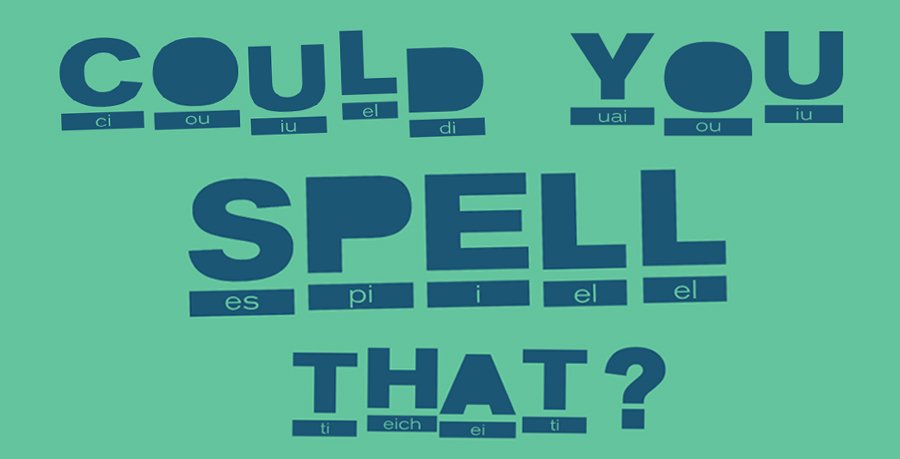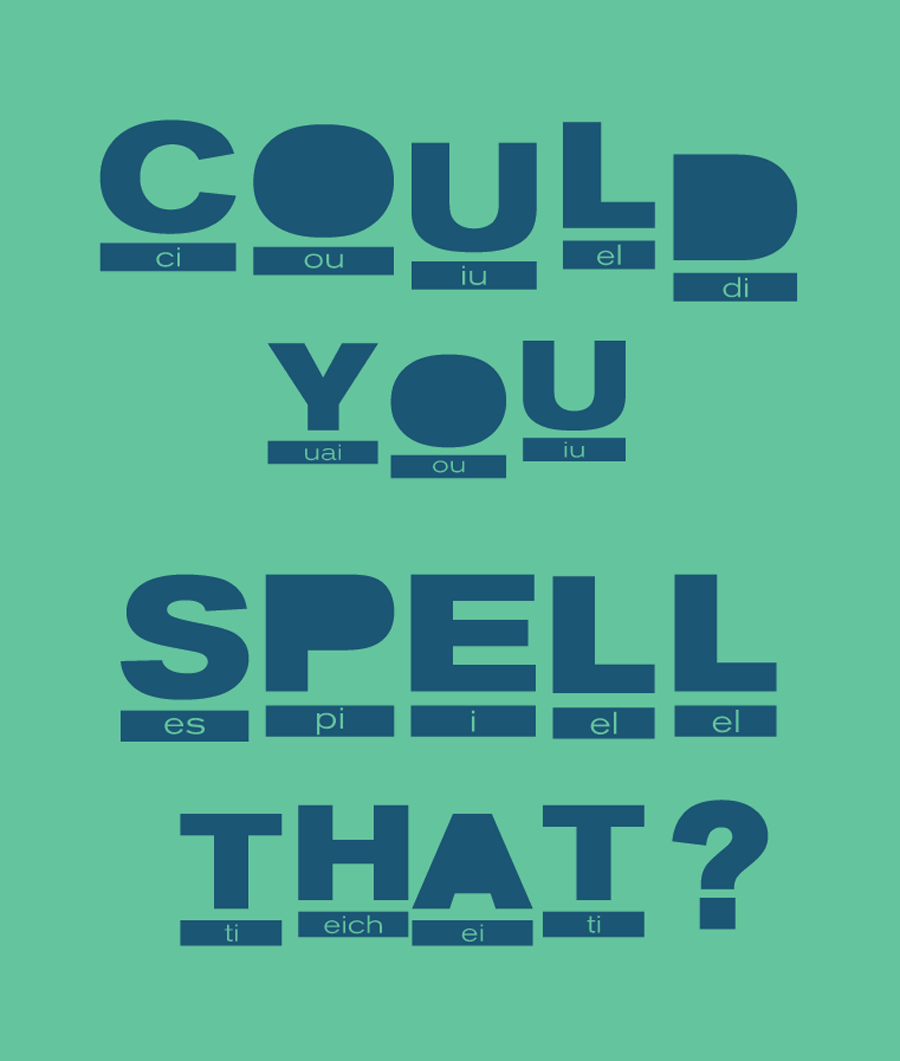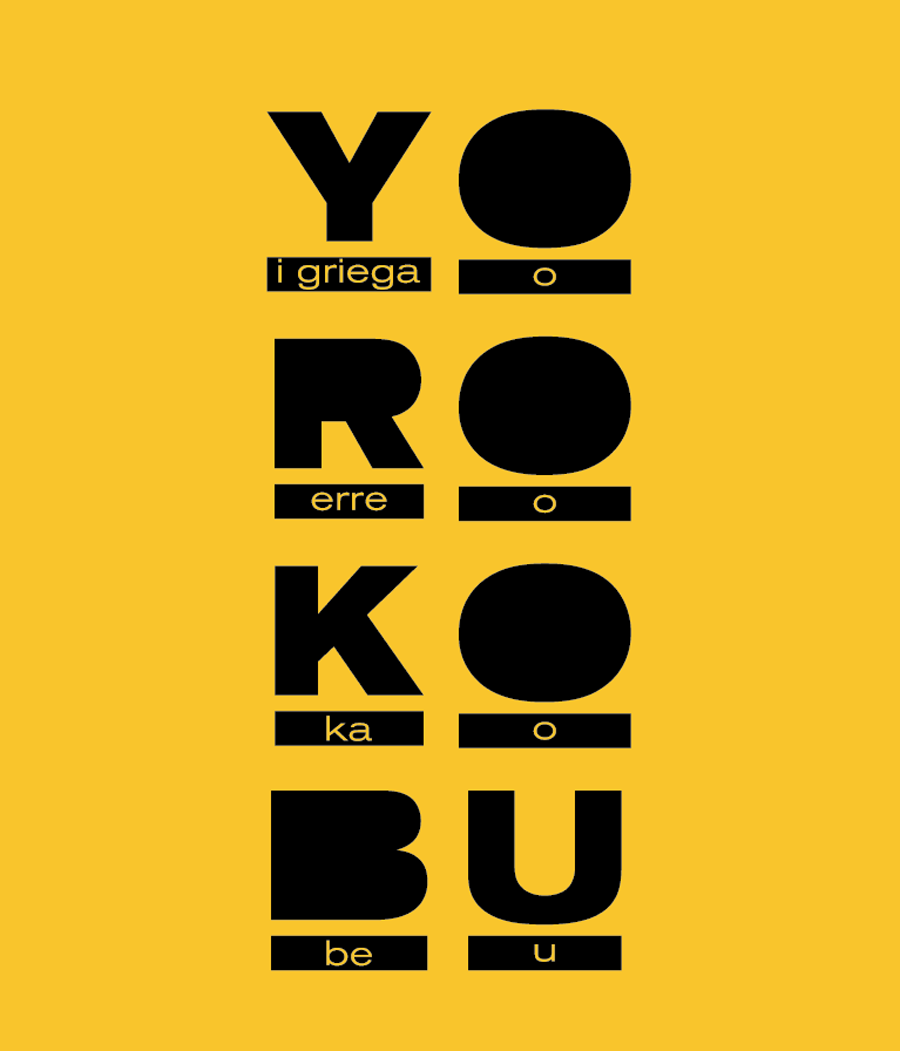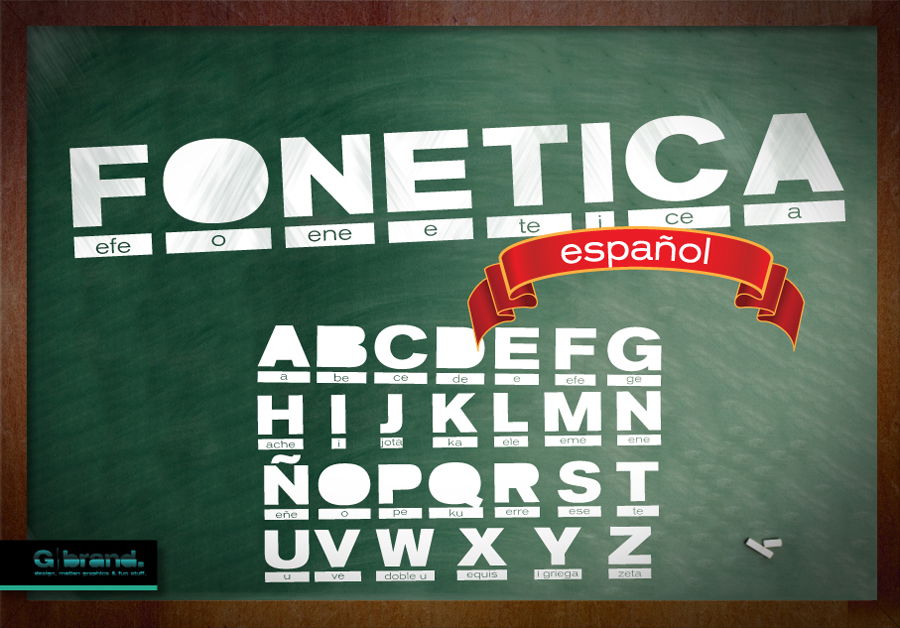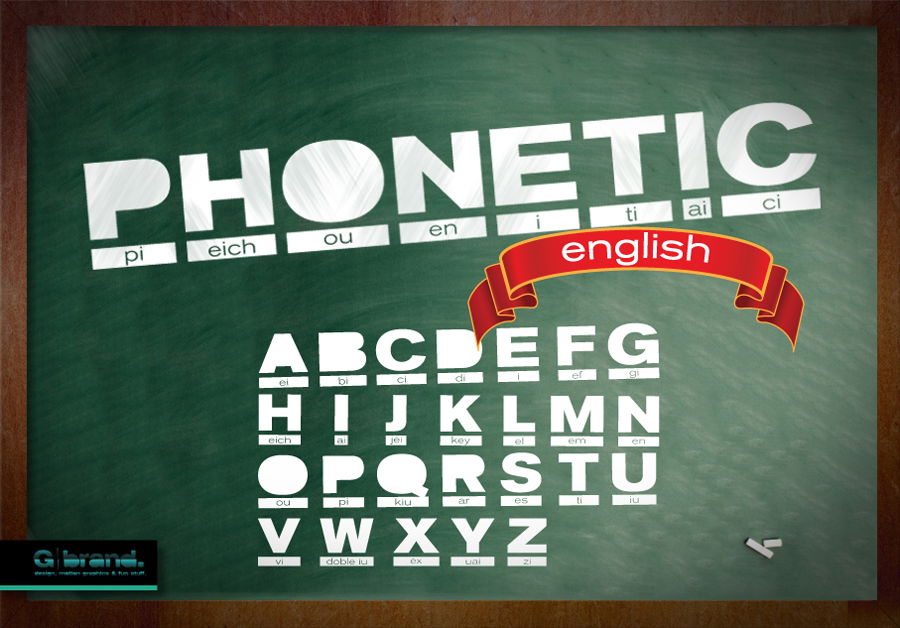
La tipografía que enseña inglés
Hay tipografías más grandes, más pequeñas, más lúgubres, más fiesteras, más anchas y más estrechas. También las hay muy ilustradas. O tan parcas que apenas se perfilan con un par de trazos. Gibrán Ramos (G Brand), un joven diseñador mexicano, ha inventado un tipo de letra para esos que siempre se liaron cuando les preguntaron aquello de “Could you spell that?” (¿Podrías deletrear eso?)
Phonetic (o Fonética) es una tipografía con intenciones de echar una mano a los que nunca contaron con el inglés entre sus fuertes. Cada letra de la fuente, además del caracter en sí, lleva de serie en su base la manera de pronunciarlo en el idioma de Shakespeare. No en fonética tradicional -que no todo el mundo sabe leer-, sino con la interpretación de los sonidos desde la pronunciación mexicana escrito con todas sus letras. Es decir, que B es ‘bi’, P es ‘pi’, Q es ‘kiu’ y la H se subraya con ‘eich’.
“A mí siempre me ha gustado explorar técnicas nuevas, aprender mas cosas”, dice este diseñador que por primera vez se ha aventurado en el mundo de las tipografías. “Se me ocurrió empezar con algo diferente porque no solo quería aportar una tipografía bonita, trataba de buscarle el giro”.
Ramos describe su creación como “un concepto simple, pero diferente”. “Es una tipografía de la familia San Serif (palo seco) a la cual le quité el blanco interno y le añadí en un rectángulo la pronunciación de la misma”. “No es nada fuera de este mundo, pero podría ser de utilidad para muchas personas, incluyéndome”.
Para que la funcionalidad de Phonetic fuera bidireccional, Ramos también creó la versión inversa, es decir, con la pronunciación fonética en castellano. Su propósito, según afirma, es que su aplicación no solo tenga “meros fines estéticos y gráficos, sino también educativos y didácticos”.
“Me gusta imaginar y me gustaría mucho ver qué tipo de diseños puede inspirar mi tipografía”, esgrime el creador, “y por otro lado, también logro imaginar a personas usando mi tipografía para enseñar o aprender a leer, o para mejorar la pronunciación y el nivel de inglés. Es una sensación muy bonita sentir que hiciste algo que es de utilidad para la gente. Pensar que mi tipografía pudiera ayudar a personas de todas partes del mundo y que mi trabajo llegue a rincones del planeta donde nunca pensé que llegaría”.
Y debe ser que sí, que la gente realmente la vio útil, porque desde que la subió a la red en febrero ya ha superado las 10.000 descargas. “La creé sin fines de lucro, y aunque están enfocadas a un público de habla hispana, recibí una donación por parte de una persona de Ucrania, donde ni siquiera se habla español”, se sorprende el autor por la internacionalización de su invento.
“La idea es aportar así un granito de arena a la infinita gama de recursos gratuitos online que uno, como proteccionista gráfico, puede encontrar. Me motivó mucho ayudar al menos un poco a mis colegas diseñadores; y aún mas allá, ayudar a la gente con ese ‘spelling’ que a menudo tanto nos cuesta pronunciar”.